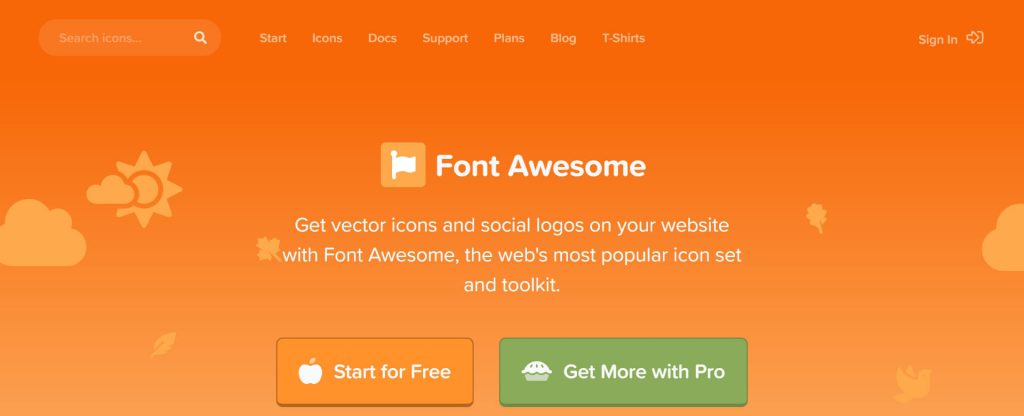
Font Awesome
Font Awesome是一套是一套绝佳的图标字体库和CSS框架,主要目的是和Bootstrap搭配使用。为您提供可缩放矢量图标,它可以被定制大小、颜色、阴影以及任何可以用CSS的样式,除此之外,还有SVG框架,流行前端库(如React)的官方NPM包以及访问新CDN等功能。
Font Awesome的产品功能
一套字库, 675个图标
FontAwesome是一种带有网页功能的象形文字语言,并收集在一个集合里。
不需要JavaScript支持
更少的兼容性问题,因为该字体不需要javascript
无限的扩展性
可缩放的矢量图形,每个图标在放大或者缩小的时候看起来都正常
CSS控制
可以轻松的用css来控制字体的颜色,大小,阴影等!
完美支持Retina屏幕
字体是矢量图,这意味着在高分辨率下也会完美显示。
良好的兼容性
最初是为Bootstrap而设计的,现在Font Awesome适用于所有框架。
兼容桌面级应用
如果你需要用于桌面软件设计或一套完整的矢量图